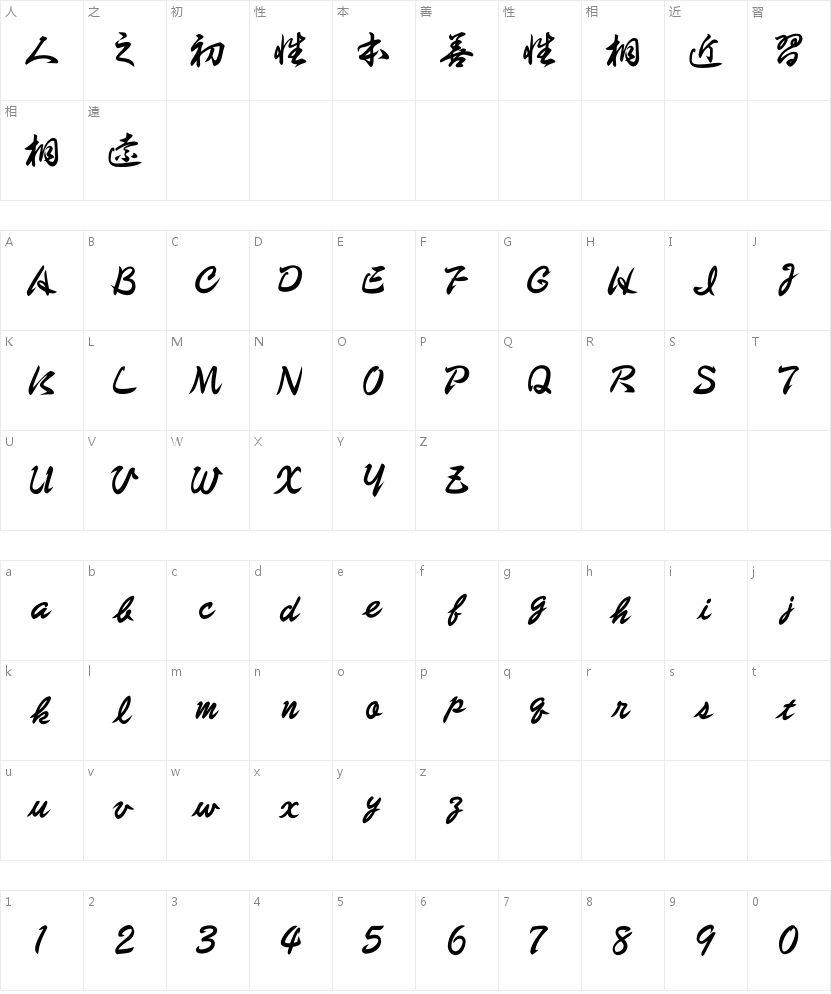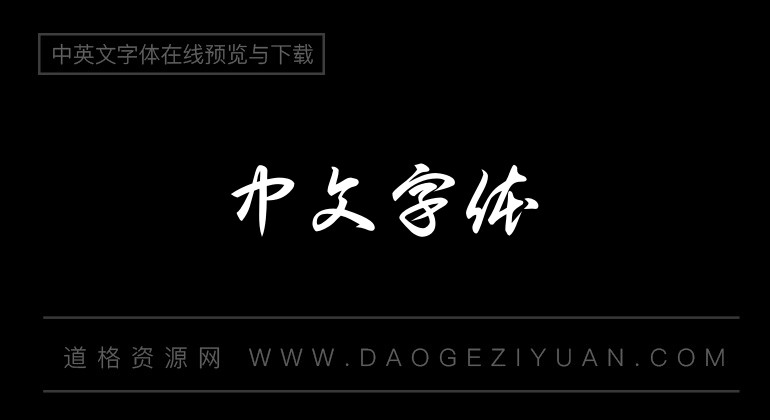
? HOT-白舟太草書 Std B 字体是一款以古典書法为基础,结合现代设计理念的字体。它拥有鲜明的書法特色,并采用现代化的笔画设计,使字体更加立体化,笔画更加细腻,给人以清新自然的感觉。它的特点是字体线条流畅,笔画细腻,字形精致,整体比例协调,极具古典气息,可以用于商业广告、书籍封面、海报设计等。文件名:HOT-FSoshoStd-B-2.otf
HOT-白舟太草書 Std B是一款非常不错的手写艺术字体,具有很好的视觉感,适合于文化类的宣传设计、商业类品牌的广告和产品包装设计以及个性化文字排版等较多场景。